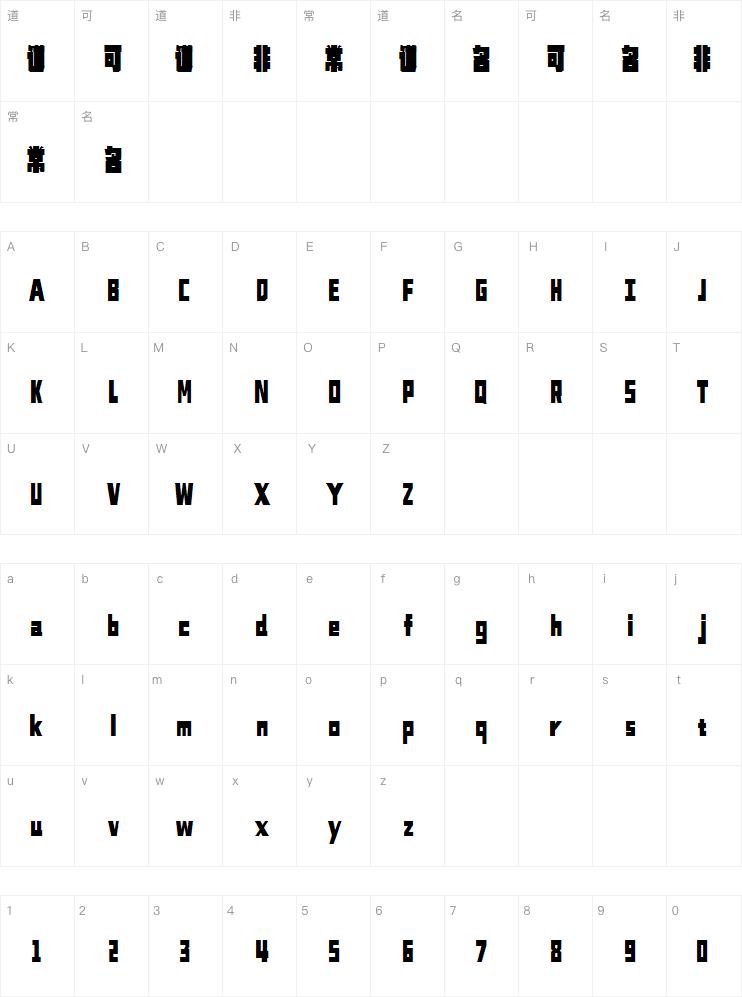
山海标题正黑w
山海标题正黑,是一款全新的字体,包含汉字9169个,符号200+个。该字体是一款综艺标题黑体字体,是一款具有强劲视觉冲击力的综艺风格标题字体。字形造型硬朗,直线和曲线的笔画构成坚实有力,简洁明了的笔画切角;字形比例按照宽高3:5的比例设计,使得字体极其瘦高;同时笔画带有切角设计,使得字形带有律动感,带来强有力的视觉冲击效果。该字体在综艺体的基础上做了诸多创新,使得该字体既有着流动的美感,又有着端肃的凝重,在正式用字场合落落大方,在日常使用环境中不失亲切友好,能够在保留综艺体基本特征的基础上更能适应当下时尚潮流的需要,助力各大新产品夺取标题主战场。